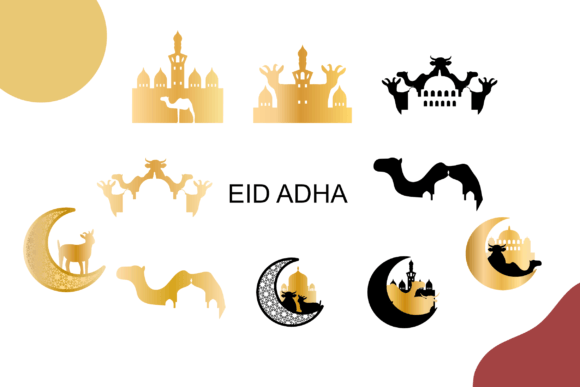
Golden Eid Adha
หากคุณกำลังมองหาเนื้อหาคุณภาพสูงเช่น Golden Eid Adha แพ็คเกจพรีเมียมนี้เป็นตัวเลือกที่ยอดเยี่ยมสำหรับโปรเจ็กต์สร้างสรรค์ของคุณ
ไม่ว่าคุณจะสร้างผลิตภัณฑ์ POD (Print on Demand) คำเชิญงานแต่งงาน หรือกราฟิกโซเชียลมีเดีย Golden Eid Adha ก็เหมาะสมอย่างยิ่ง